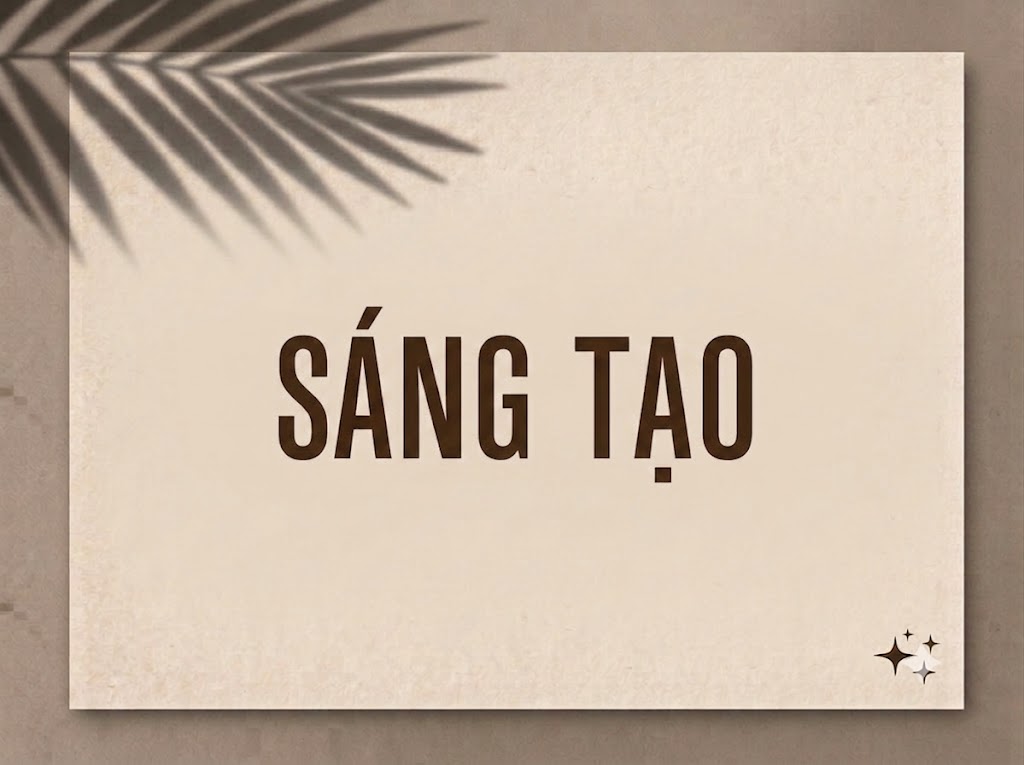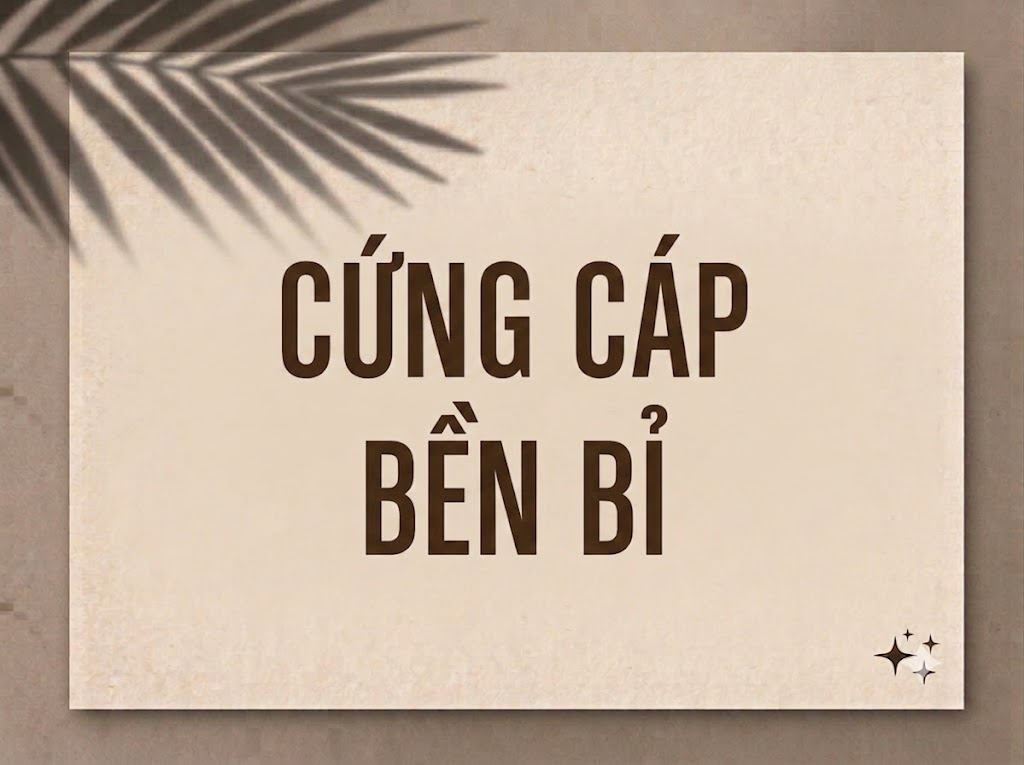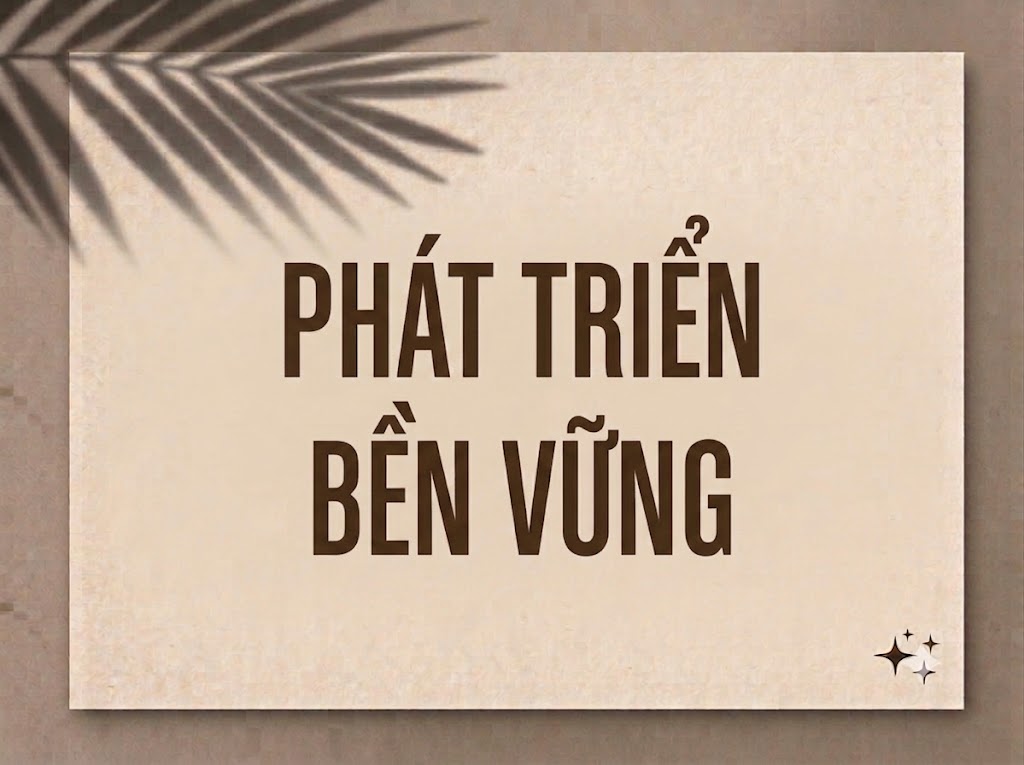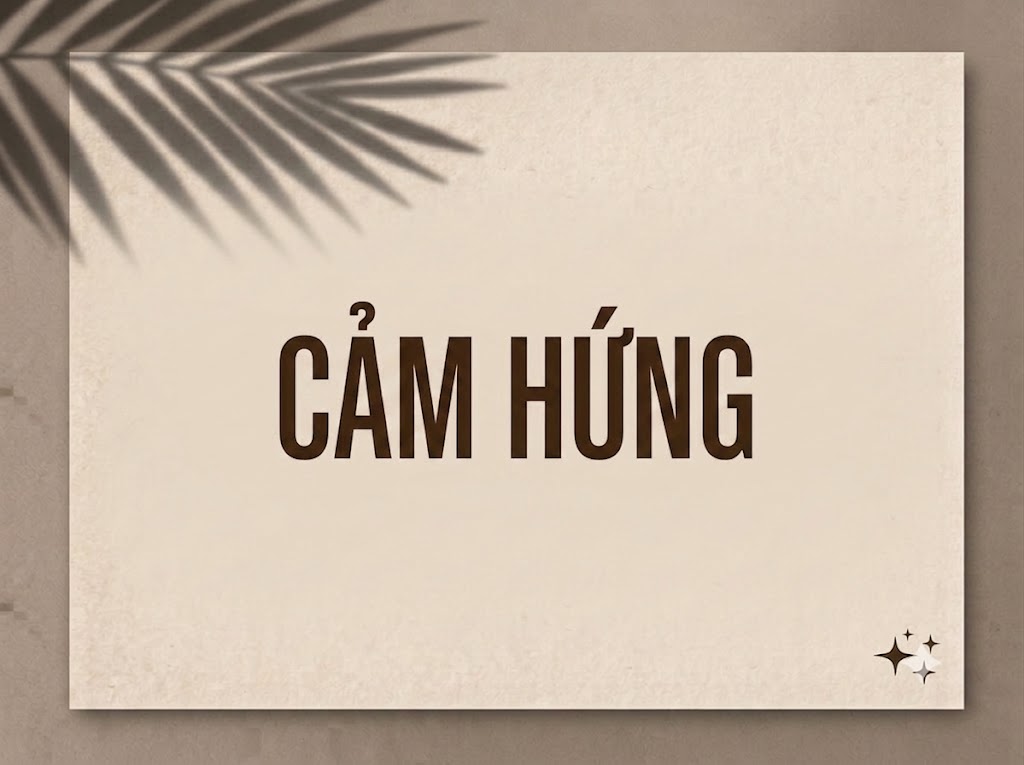
Font Việt hóa 1FTV Peghas
1FTV Peghas
Trong kỷ nguyên số, khi xu hướng tiếp cận nội dung trên màn hình dọc ngày càng thống trị, các nhà sáng tạo nội dung luôn đối mặt với bài toán: Làm thế nào để chèn những câu giật tít dài, những dòng sub quan trọng vào một không gian chiều ngang cực kỳ ngặt nghèo mà không làm giảm kích thước chữ chữ hay khiến bố cục bị rối loạn?
Những dòng phông chữ thông thường khi phóng lớn sẽ lập tức tràn viền. Đó  là lúc vũ khí bí mật mang tên Extra Condensed (siêu nén) xuất hiện. Nếu bạn đang tìm kiếm một giải pháp typographic vừa mang tính gai góc, phá cách nghệ thuật, vừa tiết kiệm không gian ngang tối đa thì font 1FTV Peghas chính là câu trả lời xuất sắc.
Giới thiệu về font 1FTV Peghas
Font 1FTV Peghas là một bộ chữ hiển thị không chân được tinh chỉnh theo phom dáng siêu nén, thuôn dài độc đáo, mang đậm tinh thần kiến trúc hiện đại và cá tính mạnh mẽ.
Đặc điểm nổi bật của phong cách thiết kế Peghas
Sức hút thị giác đặc biệt của font 1FTV Peghas đến từ cấu trúc hình khối ép chặt chiều ngang (condensed) cực hạn và kéo dài tối đa theo chiều dọc:
• Tối ưu không gian ngang cực đỉnh: Kiểu dáng siêu thuôn giúp bạn có thể sắp xếp các cụm từ dài, tiêu đề nhiều chữ trên cùng một dòng văn bản mà không lo bị tràn khung hình.
• Hỗ trợ hệ ký tự hoa – thường linh hoạt: Không giống như nhiều font display chỉ hỗ trợ định dạng All-Caps (chỉ có chữ in hoa), Peghas tích hợp trọn vẹn cả hệ thống chữ cái viết thường và chữ viết hoa đồng bộ. Cấu trúc chữ thường có chiều cao x-height rất lớn, gần như tiệm cận chữ hoa, tạo nên một nhịp điệu chữ đồng đều, ngăn nắp.
• Cá tính thô ráp, bụi bặm đầy nghệ thuật: Đường nét của phông chữ không bo tròn hoàn hảo mà mang chút gai góc thô mộc, gợi liên tưởng đến những bảng hiệu vintage, poster phim indie hoặc phong cách streetwear tự do, nổi loạn.
• Hệ thống khoảng cách giữa các chữ (kerning) và độ giãn dòng (tracking) được tính toán khoa học, giúp các chữ cái khi đứng sát nhau trong phom dáng nén vẫn giữ được khoảng hở thẩm mỹ tối thiểu, đảm bảo độ rõ ràng, không bị dính nét hay gây ngột ngạt khi đọc nhanh.
• Tích hợp đầy đủ bộ ký tự hoa – thường, dãy chữ số từ 0-9 phom thuôn đứng ngay ngắn cùng hệ thống các ký tự đặc biệt, dấu câu thông dụng (1234567890.:,;'"(!?)+-*/=).
Hình ảnh demo thực tế của font 1FTV Peghas
• Kích thước nhỏ (12pt – 24pt): Nhờ kết cấu đường nét đứng ngay ngắn, các khối chữ viết thường và chữ số vẫn hiển thị rất sắc nét, ngay hàng thẳng lối và cực kỳ dễ đọc trên giao diện màn hình di động cỡ nhỏ.
• Kích thước lớn (36pt – 72pt): Đây là đất diễn lý tưởng nhất để font phô diễn toàn bộ sự độc lạ, mạnh mẽ của phom dáng siêu nén, tạo tác động thị giác cực mạnh cho các dòng tiêu đề chính.
Ứng dụng của font Peghas trong thiết kế đồ họa và biên tập video
Sở hữu nét cá tính độc lạ, siêu nén tối ưu không gian và cấu trúc hoa – thường linh hoạt, font 1FTV Peghas mở ra không gian sáng tạo vô cùng rộng lớn cho các ấn phẩm truyền thông hiện đại:
• Làm tiêu đề cho video ngắn (TikTok, Reels, Shorts): Dáng chữ thuôn hẹp theo chiều dọc này sinh ra là để dành cho khung hình đứng 9:16 của thiết bị di động. Nó giúp bạn thoải mái chèn những câu giật tít, cụm từ khóa chính siêu dài ở phần mở đầu video mà không lo bị tràn viền hay che khuất các chủ thể quan trọng trong khung hình.
• Thiết kế ảnh thu nhỏ mạng xã hội (Thumbnail): Đây là vũ khí tuyệt vời để tạo nên những chiếc thumbnail YouTube, TikTok độc lạ cho các kênh thuộc chủ đề thời trang đường phố (streetwear), kiến trúc tối giản, vlog đời sống bụi bặm, review phim ảnh hoặc âm nhạc underground nhằm kích thích tỷ lệ nhấp chuột.
• Banner quảng cáo và Poster phim nghệ thuật: Hoàn hảo cho các poster phim độc lập, banner chương trình âm nhạc alternative, hội chợ ngoài trời hoặc các chiến dịch marketing kỹ thuật số cần sự tối giản về không gian nhưng tối đa về phong cách thị giác.